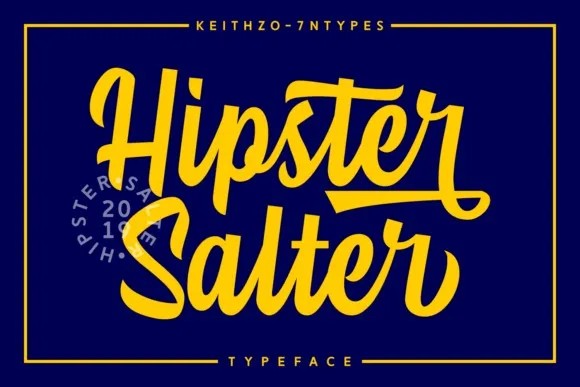
Esta é uma fonte script poderosa e estilizada, criada pelo designer Keithzo (7NTypes) no ambiente da plataforma 99designs. Ela foi cuidadosamente feita com letra à mão e contém muitos alterações de estilo e desenhos de ponta que lhe darão a liberdade para criar seu próprio design único. Ideal tanto para aplicativos digitais quanto para impressão, esta fonte script irá deixar suas criações em alta. Se você está procurando uma opção que combine modernidade com um toque pessoal e elegante, essa é a escolha perfeita.